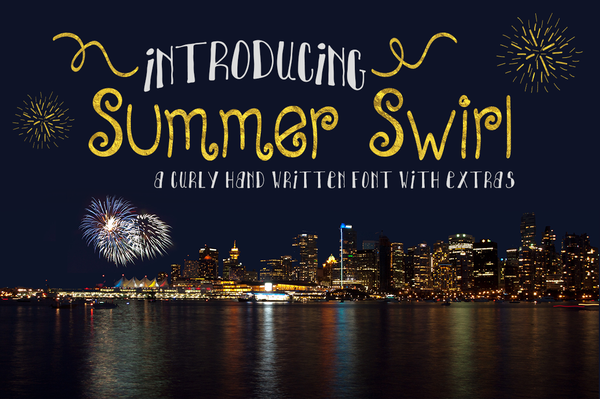
Summer Swirl Font
Descubra a fonte Summer Swirl neste emocionante set de caracteres playfull. Desenvolvida pelo designer Hamilton, esta fonte combina formas levemente distorcidas com traços curvados, criando um efeito que parece dançar nas palavras escritas. Se você está procurando por uma fonte divertida para tornar seus projetos mais alegres e vivos, Summer Swirl é o tipo perfeito para você. Sua versatilidade permite usá-la em tudo desde cartazes e letras de música até editoriais e ilustrações animadas. Para conhecer melhor esta maravilha tipográfica e acessar extras interessantes, visite a página da fonte no nosso site: https://www.milliemaeandco.com/collections/fonts .